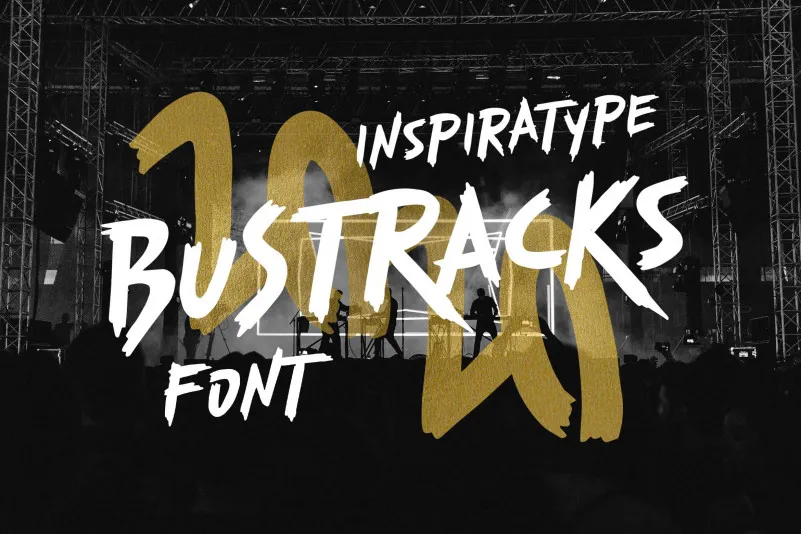
Bustracks Font – Download Grátis
A Bustracks Font é uma tipografia de exibição desenvolvida à mão, inspirada nos clássicos anúncios que marcaram a história da publicidade. Este desenho moderno e vibrante captura a essência de um tempo passado, mas oferece um toque contemporâneo através dos detalhes meticulosamente cuidados. Se você é fã de tipografias inspiradas em materiais vintage ou busca uma maneira criativa de incorporar elementos nostálgicos em seu projeto, essa fonte será perfeita. Inspirasign, o designer por trás desta criação, certificou-se de manter um equilíbrio entre a simplicidade dos anúncios tradicionais e uma personalização sofisticada que faria jus à sua função. Não importa se você está projetando letras em postais antigos ou criando novos elementos para seus websites, a Bustracks Font traz um toque memorável de nostalgia ao seu trabalho.